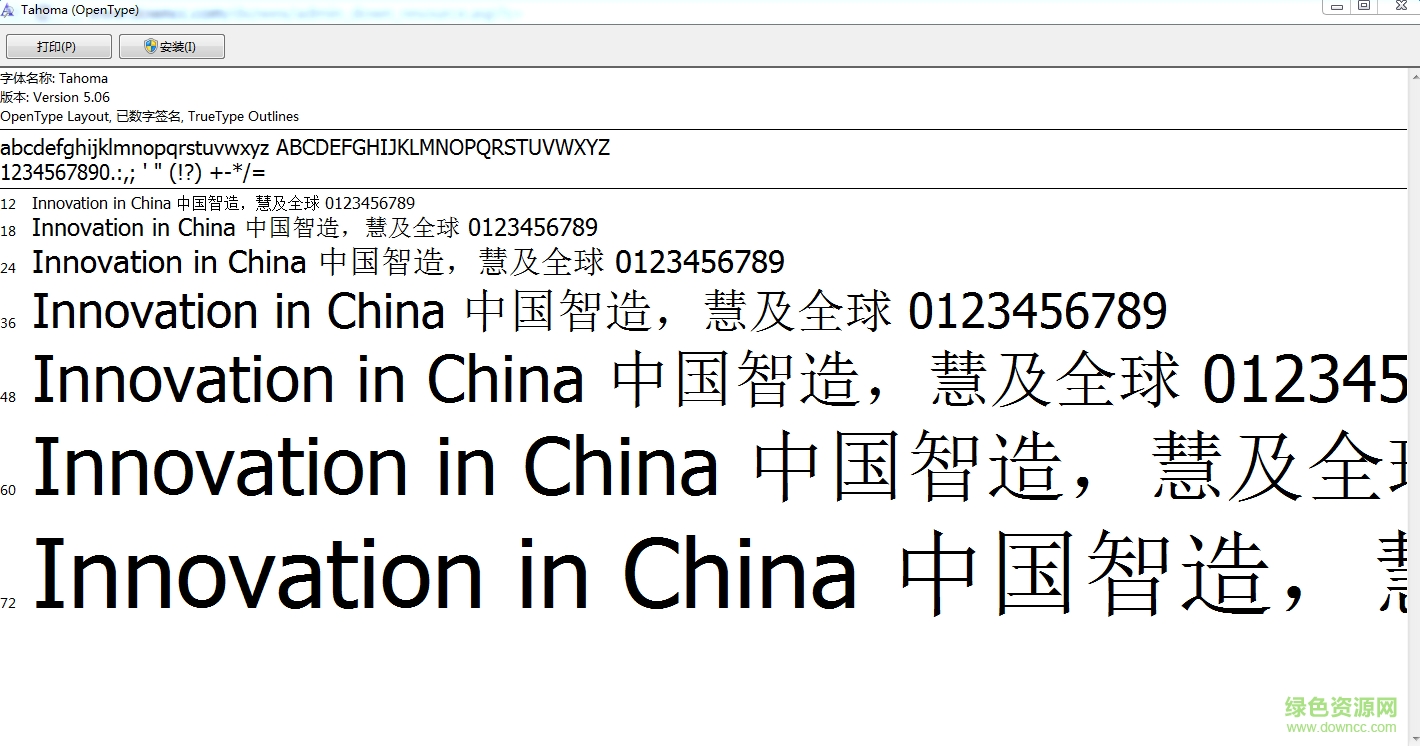
Tahoma是一種十分常見的無襯線字體,Tahoma和Verdana師出同門,同為名設(shè)計(jì)師馬修·卡特的作品,由微軟在1999年推出。許多不喜歡arial字體的人常常會改用Tahoma來代替,除了是因?yàn)門ahoma很容易取得之外,也是因?yàn)門ahoma沒有一些Arial為人詬病的缺點(diǎn),例如大寫“I”與小寫“l(fā)”難以分辨等。Tahoma被采用為Windows 2000、Windows XP、Windows Server 2003及Sega游戲主機(jī)Dreamcast等系統(tǒng)的默認(rèn)字型。
1.Tahoma是種非常圓滑的字體。
2.字體結(jié)構(gòu)和Verdana很相似,其字符間距較小,而且對Unicode字集的支援范圍較大。
3.這個(gè)字體比較均衡,中英文混排顯示時(shí),不會出現(xiàn)中英文不對齊的狀態(tài)。